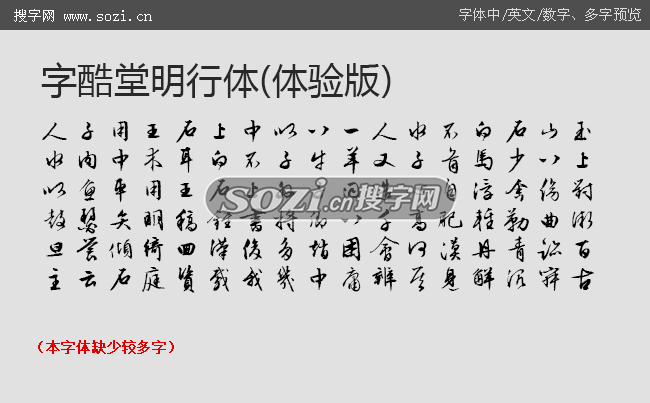
字酷堂明行體(體驗(yàn)版)
搜字網(wǎng)提供一款字酷堂明行體(體驗(yàn)版)手寫中文書法字體下載,字酷堂明行體是一款非常漂亮的手寫字體,字體極具藝術(shù)風(fēng)格,每筆每畫都給人一種飄逸灑脫的感覺,整體效果非常出色,能夠應(yīng)用于平面設(shè)計(jì)、名片設(shè)計(jì)、廣告創(chuàng)意、印刷等場合應(yīng)用。